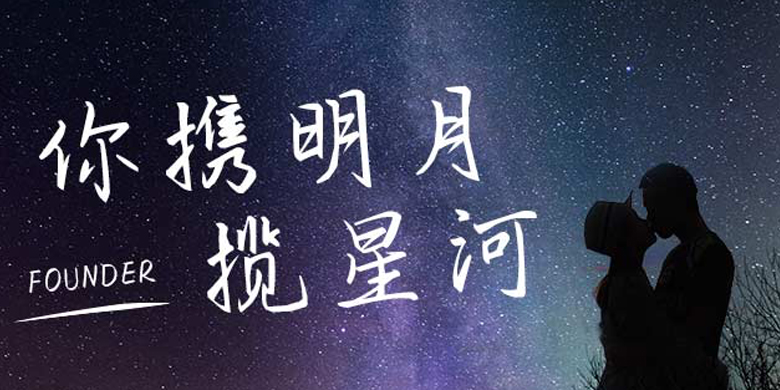
方正手迹-你携明月揽星河
字体品牌: 方正手迹 设计师:尚正中 字体分类:常规书写·硬笔 字体属性:精品字 字符集:大陆简体(GB2312-80) 发布时间: 2020
一款舒适度超强的手写楷体,中宫宽松,收笔有秩,粗细对比适当,结构严谨。适用于文艺类的书刊、品牌广告和产品包装设计,以及社交网络的个性化用字。